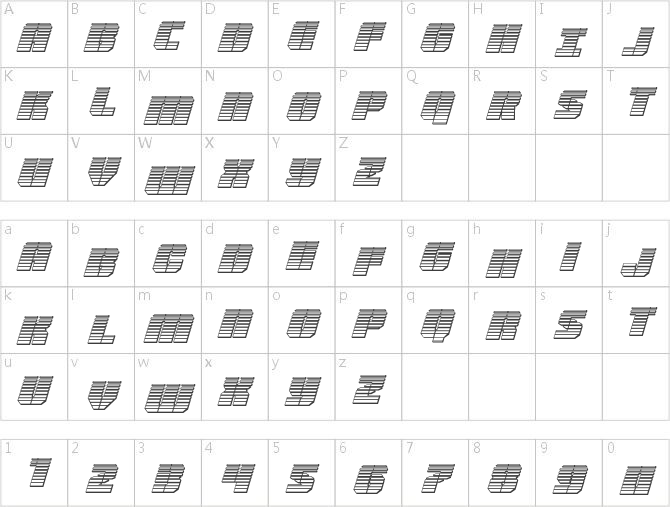
Warp Thruster Chrome Italic
Warp Thruster Chrome Italic介紹
Warp Thruster Chrome Italic字體字庫是一款讓人賞心悅目、百看不厭的英文字體,適合各類廣告和產品包裝設計應用,字體大小0.11MB,格式為ttf字體,上傳用戶是ㄚòひ慬偶鰢,作者/版權方為未知